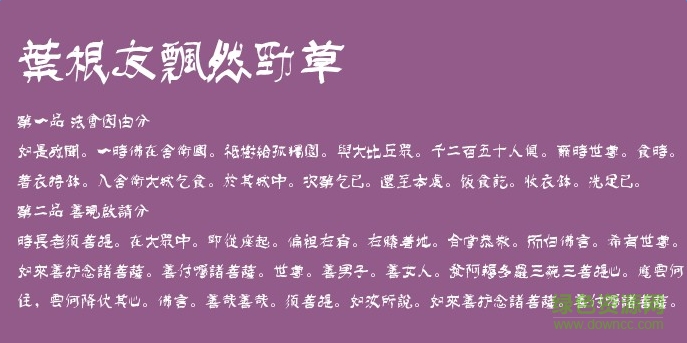
葉根友飄然勁草字體是一款放蕩不羈草書風(fēng)格字體軟件,本款字體以繁體呈現(xiàn)在用戶面前,有著濃厚的書法氣息,整體效果非常古典文雅,得到廣大書法家的喜愛和贊美,還有更多好看字體歡迎來綠色資源網(wǎng)下載體驗(yàn)!
葉根友飄然勁草字體是一款設(shè)計(jì)類的字體 其字跡清晰 帶有意思飄然的感覺,這也是增加了傳統(tǒng)的創(chuàng)意,而且這個(gè)字體還有一些中國風(fēng)在里面,很適合一些作家使用。
該字體以草書的形式配上中國古典繁體,字體效果令人堪奇,非常的漂移灑脫,藝術(shù)氣息十足!